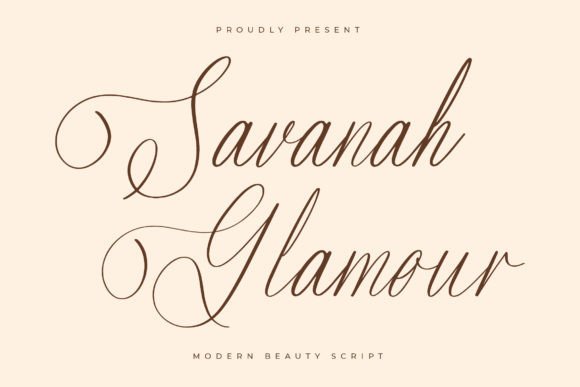
Savanah Glamour
適切なデザイン要素を見つけるのは難しい場合がありますが、Savanah Glamourは作品を即座に引き立てる優れたコレクションを提供します。
POD(オンデマンド印刷)製品、結婚式の招待状、またはソーシャルメディアのグラフィックを作成している場合でも、Savanah Glamourは理想的です。